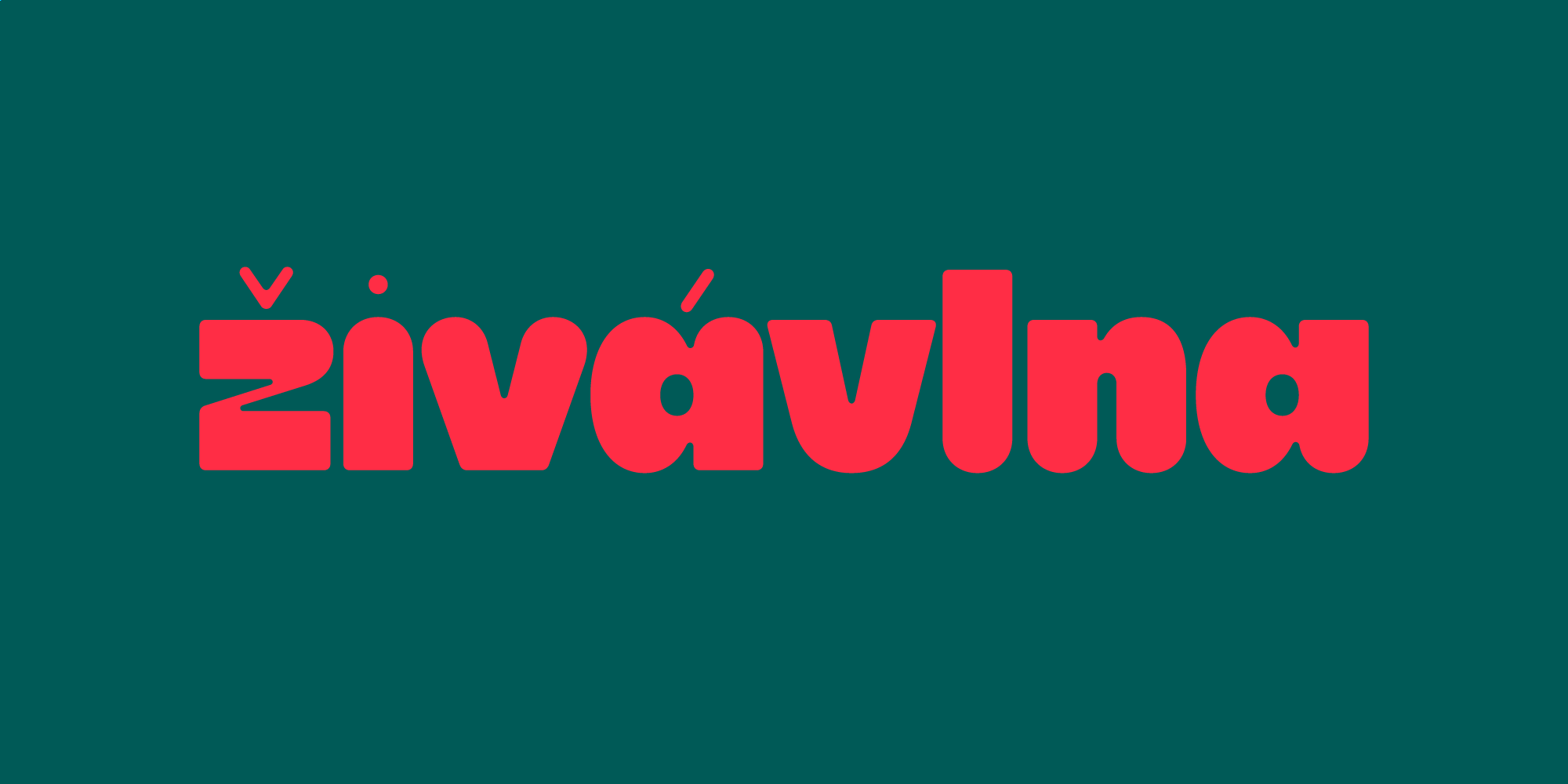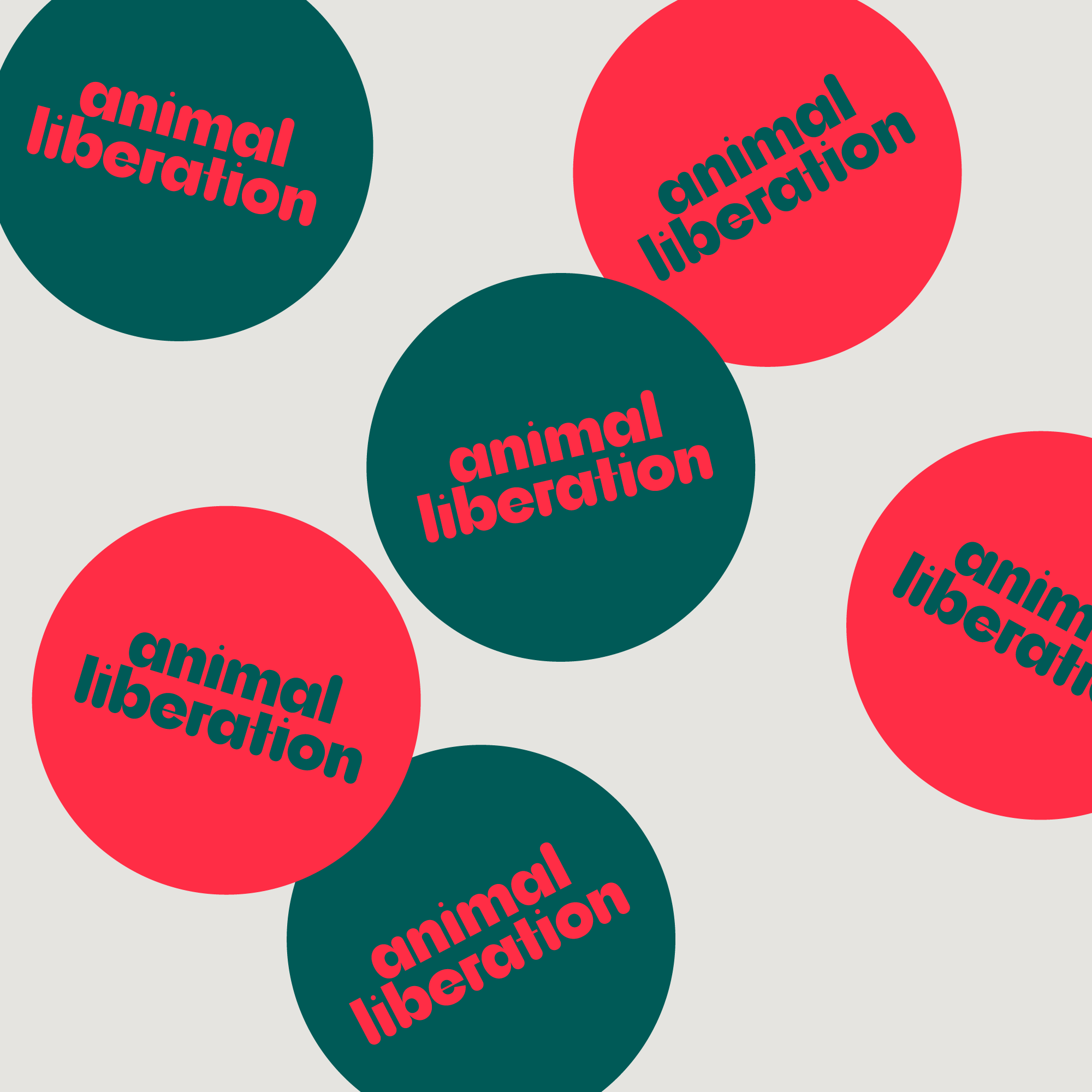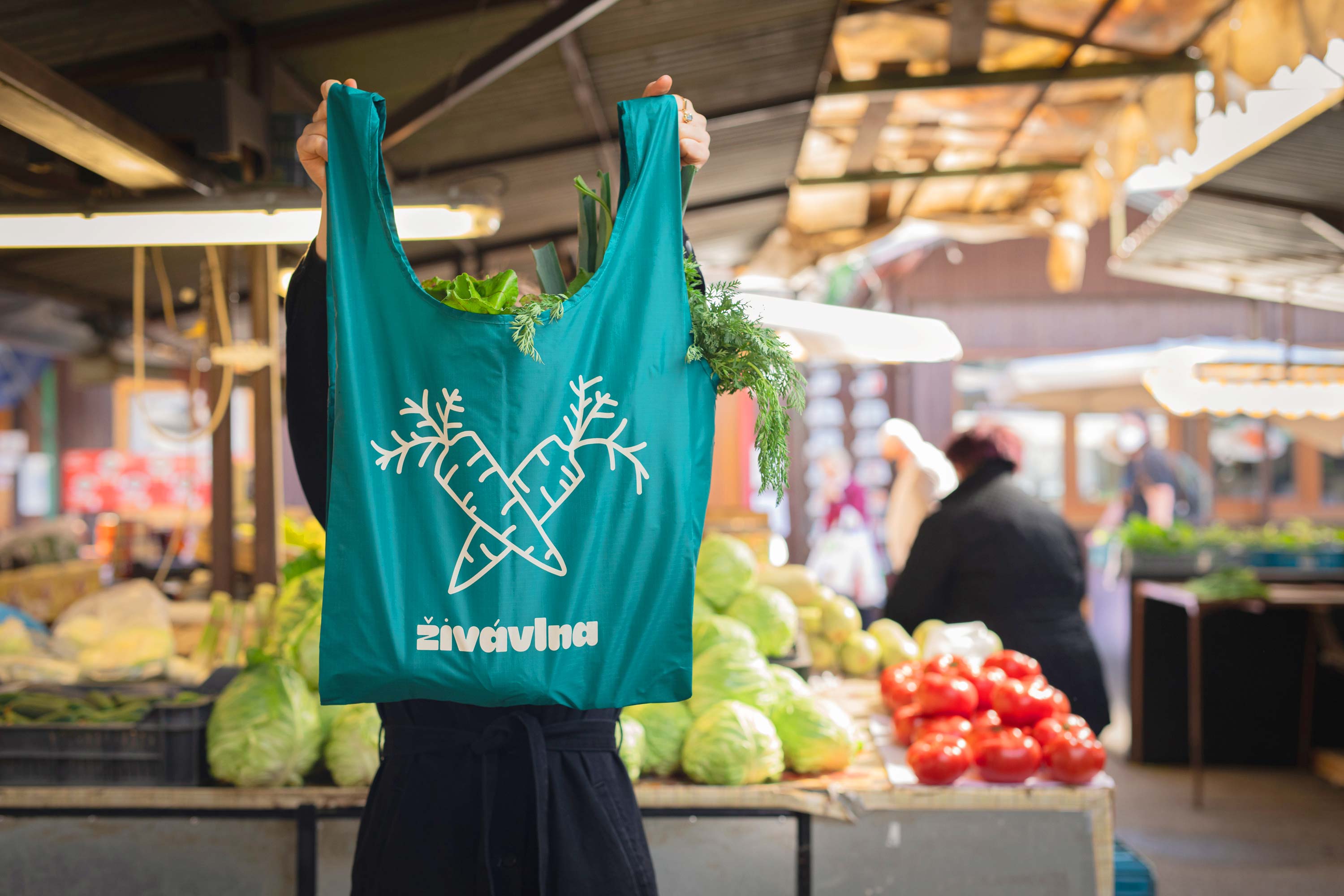
Živá vlna
Logo pre Živú vlnu, iniciatívu, ktorá sa zasadzuje za spravodlivosť pre zvieratá, prírodu i ľudí. Formou vzdelávania – článkov, tvorby a fotografií sa snaží poukazovať na vykorisťovanie zvierat v mnohých odvetviach a inšpirovať ľudí k spravodlivejšiemu a súcitnejšiemu spôsobu života ku všetkým žijúcim tvorom na planéte.
Organické logo so zaliatymi vnútornými rohmi je modifikáciou zatiaľ nebublikovaného variabilného písma štúdia Setup Type.